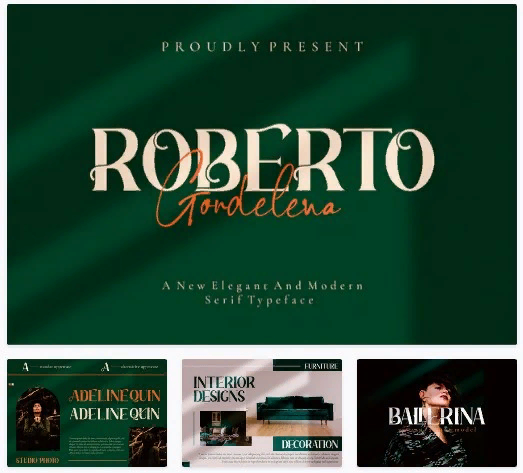
[Elements.Envato] Roberto & Gordelena Signature Font (2021)
Название: Roberto & Gordelena Signature Font (2021)
Roberto & Gordelena Signature - стильный дуо-лигатурный шрифт Display Serif, вдохновленный знаменитым минималистским логотипом, идеально подходит для целей дизайна шаблонов, брошюр, видео, рекламного брендинга, логотипов и многого другого.